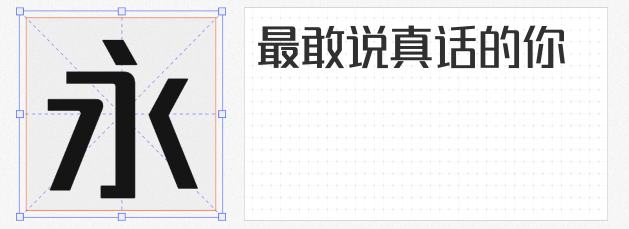
在平面设计与品牌视觉中,黑体因其简洁现代的视觉特征,成为标题、海报及品牌标识的首选。本文精选四款免费商用黑体,兼顾功能性与艺术性,助力设计师高效完成创意表达。
锐字潮牌真言简2.0以“刚柔并济”为核心设计理念,笔触浑厚有力,笔画转折处融入圆角设计,既保留传统黑体的端正凝练,又增添现代潮流感。其直角与圆角的错落搭配,使字体在视觉上更具张力,适用于品牌LOGO、综艺字幕及电商海报等场景。该字体支持可变技术,设计师可通过调节字重实现动态视觉效果,满足多媒介适配需求。
由Adobe与Google联合推出的思源黑体,是开源字体领域的里程碑之作。字体结构平衡,笔画粗细适中,适用于金融、科技等领域的商务文档、发布会PPT及品牌物料设计。其开源属性更使其成为全球设计师的“零成本解决方案”。
江城正君体400W基于未来荧黑改造,通过横向减细、纵向增粗的调整,优化了数字“4”“7”及字母“K”“k”的形态,提升整体视觉协调性。其字形简洁有力,适用于标题设计、印刷品排版及UI界面。该字体支持Windows与Mac系统安装,但需注意暂不支持手机端直接应用,适合桌面端设计项目。
句读黑体Hans以开源协议SIL Open Font License 1.1发布,支持汉字、假名、谚文、藏文、拉丁文、希腊文等多语言混排,满足全球化设计需求。其UI版本采用等宽数字设计,适配界面排版;常规版本则保留开放字怀,增强阅读舒适度。该字体适用于多语言网站、教育类APP及文化宣传物料,其开放性使其成为跨国项目的理想选择。
四款黑体各具特色。设计师可根据项目需求,灵活选择,实现创意与效率的平衡。